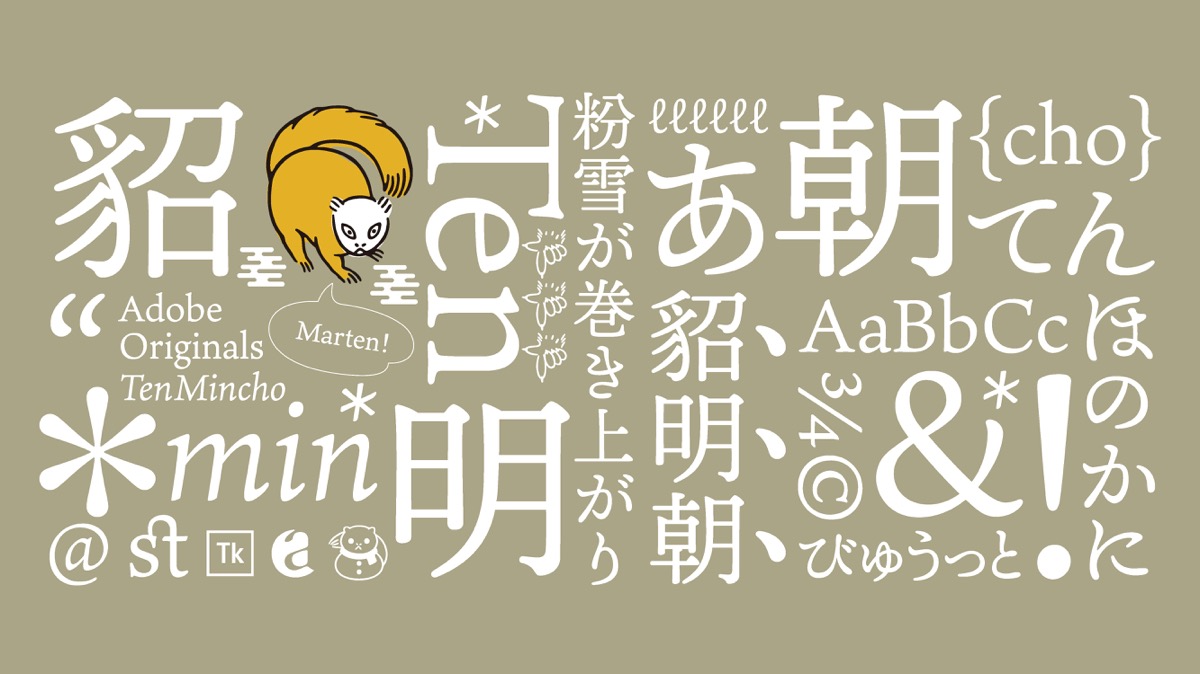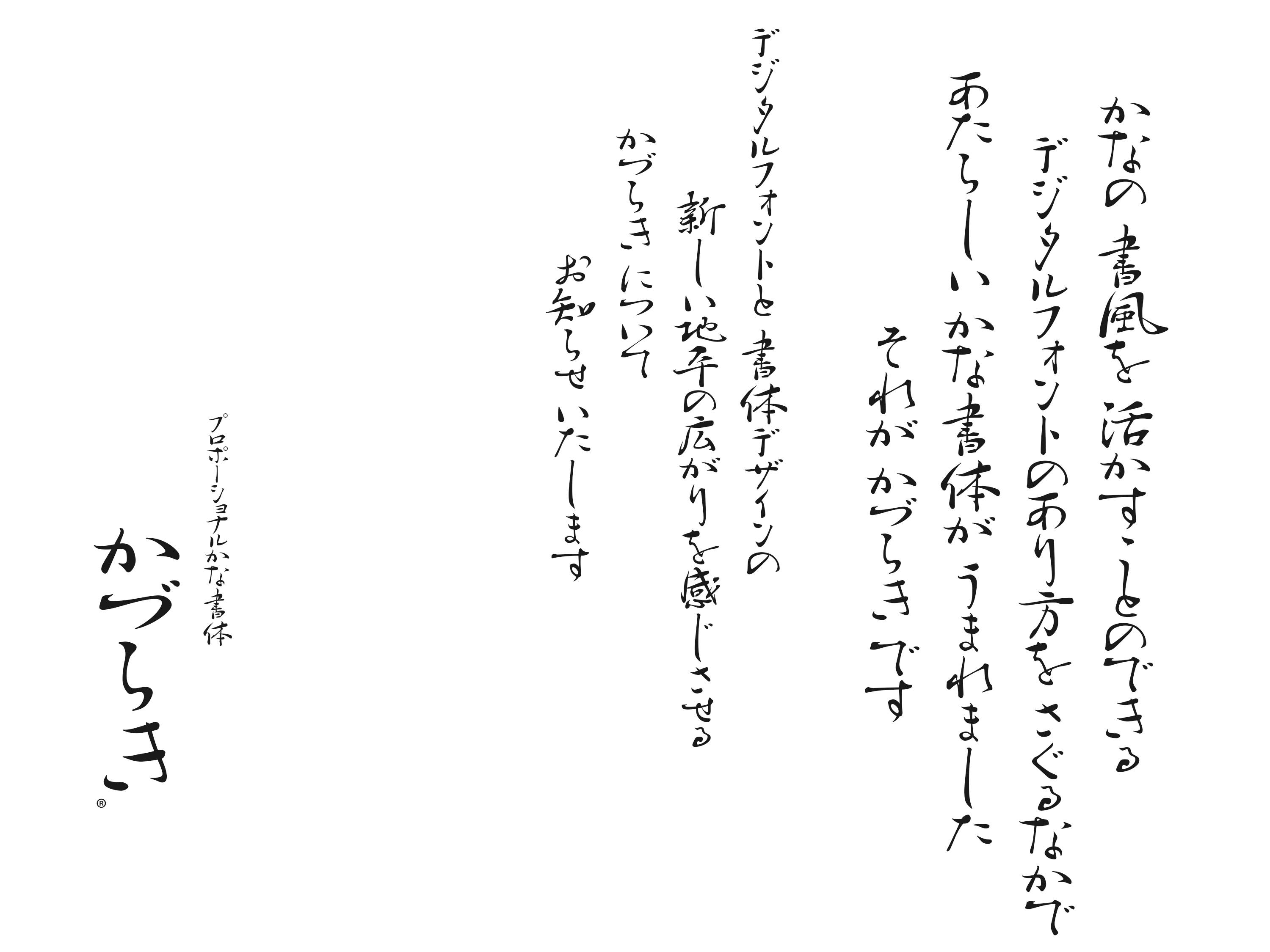
「フォントをデザインする」ことを生業にしている人が、世の中にどのくらいいると思いますか?
アドビで、日本語タイポグラフィをデザインするは、世界でも数少ない「タイプフェイス デザイナー」です。1997年にアドビに入社して以来、彼女がつねに望んでいたフォントのデザインという仕事に情熱と誇りをもって取り組んでいます。
「私は大学で書体デザインを学び、 卒業後はパッケージやポスターのグラフィックデザイナーとしてデザイン会社で働いていましたが、自分のキャリアを次のレベルに引き上げながら情熱を追求したいと考えて、アドビに入社することを決めました。」と西塚は言います。
これまで「かづらぎ」「りょう Text」「りょう Display」「りょうゴシック」などのフォントをデザインし、最近では「源ノ角ゴシック」「源ノ明朝」を次々とリリースしました。各フォントには、簡体字中国語、繁体字中国語、日本語、韓国語のスクリプトをサポートするために、6万5千字を超える文字が含まれています。
西塚は、クリエイティブツールを提供する、35年以上の歴史あるアドビにおいてユニークなポジションにいながら、最先端な技術を駆使して新たなクリエイティビティに挑んでいます。「学ぶことは過去からしかできません。闇雲に新しいことを追求していくことがクリエイティブではなく、過去の先人たちが作り上げた伝統を発展させることがクリエイティブだと思っています。」
西塚をより詳しく知るために、彼女のインスピレーションと仕事のプロセスについて聞きました。
私はフォントのデザインに集中して仕事をしていますが、フォントはそれだけではできません。アドビには有能なエンジニアがいて、彼らの力で品質の高いフォントに仕上げられますし、新しい表現のアイデアを一緒に考えることもできます。このコラボレーション文化を通して、私がやりたいことを実現できるところです。
日本の伝統の中にあるかわいさである、「鳥獣戯画」などからインスピレーションを受けた「貂明朝」というディスプレー書体をデザインしました。コンピューターの無い時代の人たちの方が圧倒的に文字を書いており、筆跡がとても豊かです。私は、その人たちの書いた昔の書体や文字に見られる筆跡にいつも魅了されています。
日頃から、書体をデザインする際はユーザーの観点から考えるのが好きです。アイデアが浮かんだら、ニーズに合ったスタイルをスケッチしていきます。基本的に手の動きを重視していますので、もちろん紙にも描きますが、Adobe Sketchを使ってiPadに描く場合もあります。そこからイメージを固めてデータにしていきます。
日本語は漢字が多いので、だいたい2年くらいかかるものが多いです。文字数が少ないフォントの場合は一気に作ってすぐリリースするのではなく、複数同時進行で交互に作っている場合が多いので、結果そのくらい時間がかかってしまうのです。時々、プロジェクトに触れない時間を作ることによって客観的に見ることができ、品質をあげることができると考えています。
バリアブルフォントやカラーフォントなどが出始めているように、新しいテクノロジーとの融合により新たな表現方法が生まれています。まだ文字数の多い漢字圏はフルサポートできてはいないのですが、近いうちに実現すると思います。そこにどのようなデザインを合わせていくのかを私も模索しているところです。
「融合」 ですね。過去と最先端の技術が結びついて新しい表現が生まれたときに、いつも心が躍ります。また新たな表現のフォントを開発中ですので、是非ご期待ください。